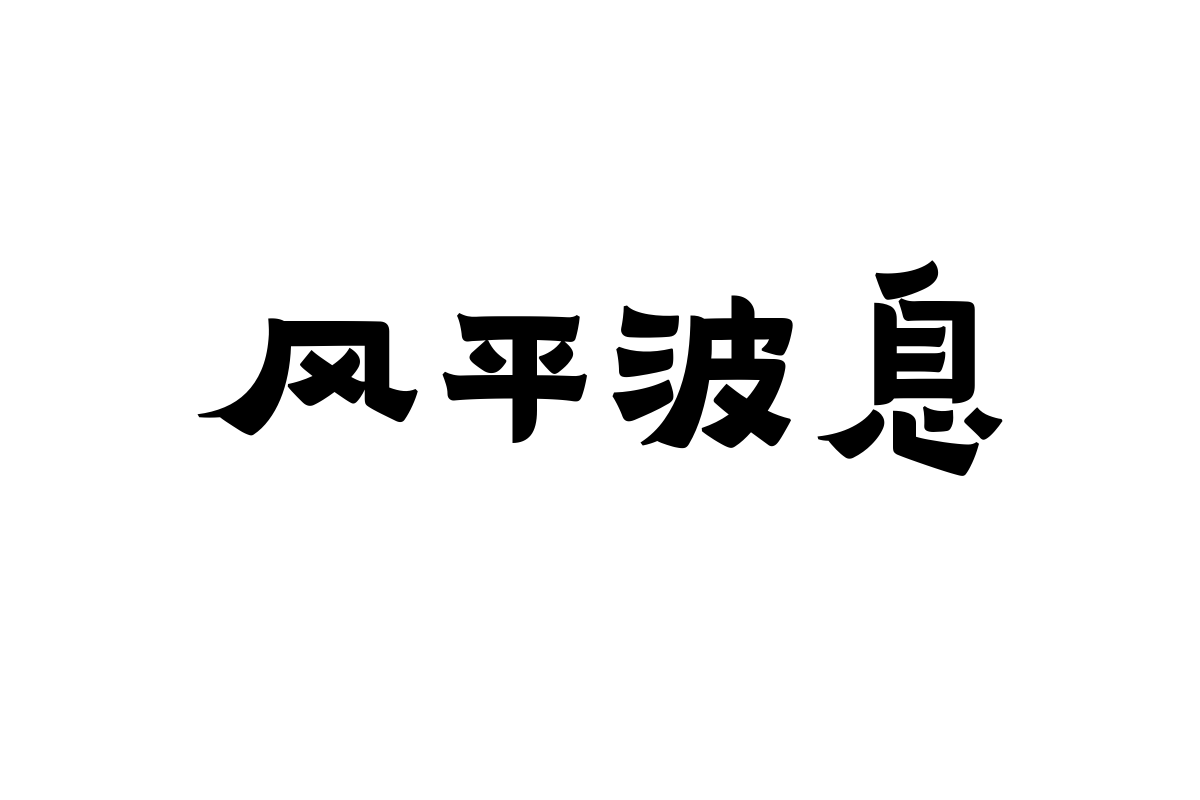
汉仪飞檐隶体是一款具有现代感的书法字体,它以简洁、流畅的线条和优美的字形为特点。这款字体的设计灵感来自于传统的隶书,但又融入了现代审美的元素,使得它既有古典韵味又不失时尚感。
汉仪飞檐隶体的笔画粗细适中,线条清晰有力,给人一种刚健而不失柔美的感觉。它的字形结构紧凑,但又能展现出一种轻松自如的美感。这种独特的风格使得它在书法作品中能够展现出独特的魅力。
此外,汉仪飞檐隶体还具有一定的适应性,无论是用于书写还是用于设计,都能呈现出良好的效果。它适合用于各种场合,如书法作品、广告设计、包装设计等,都能展现出其独特的美感和实用性。
总的来说,汉仪飞檐隶体是一款非常优秀的书法字体,它以其独特的风格和实用性,受到了广大设计师和书法家的喜爱。